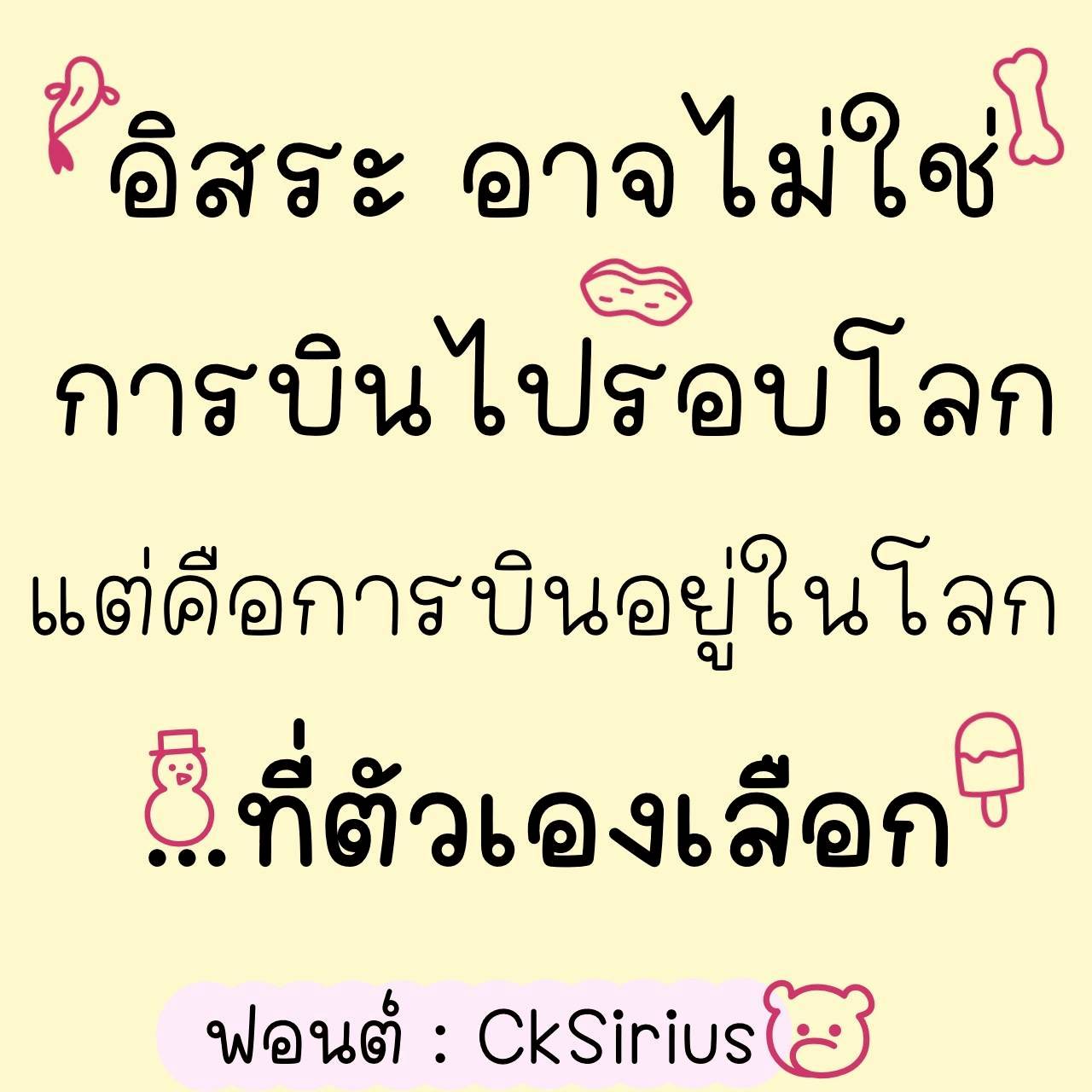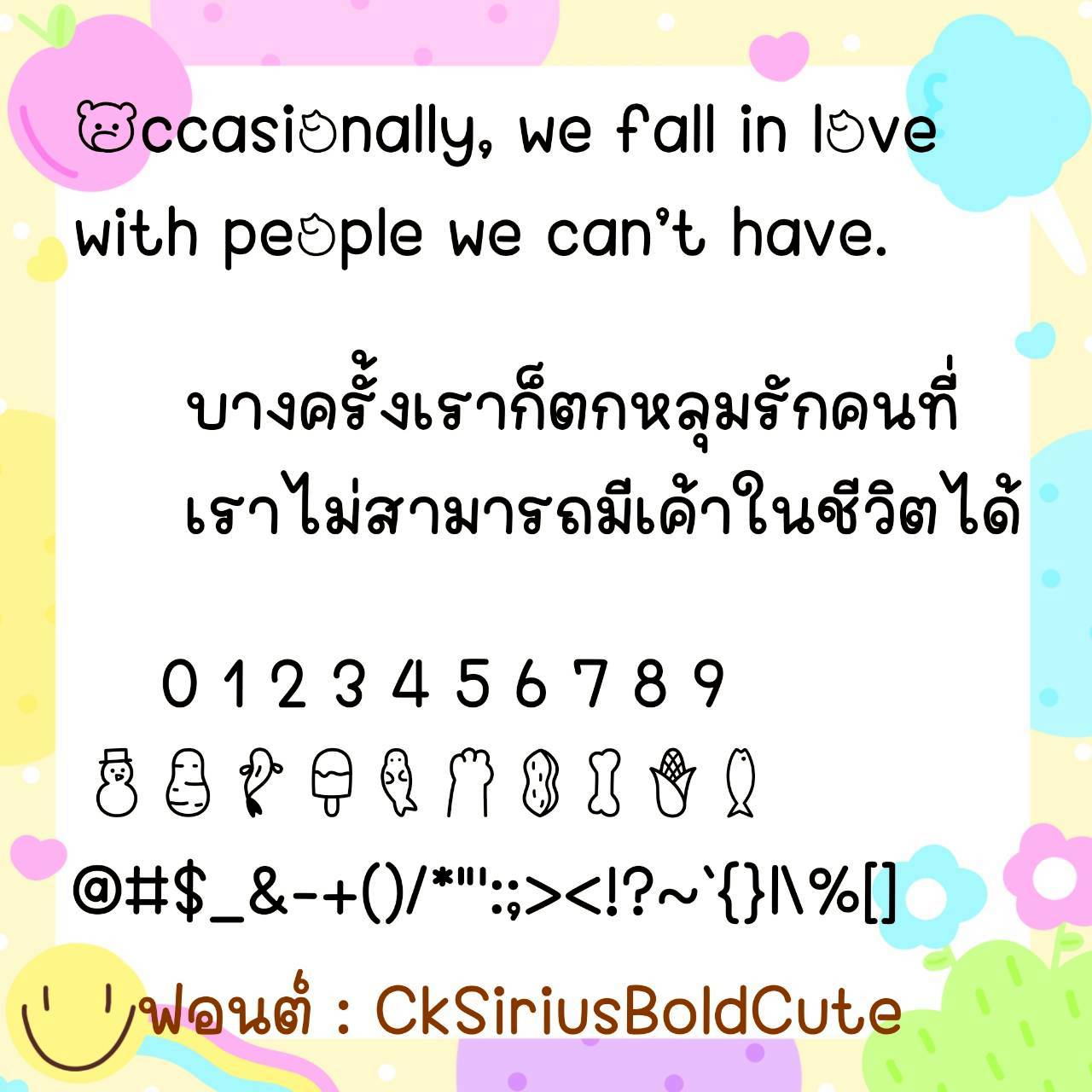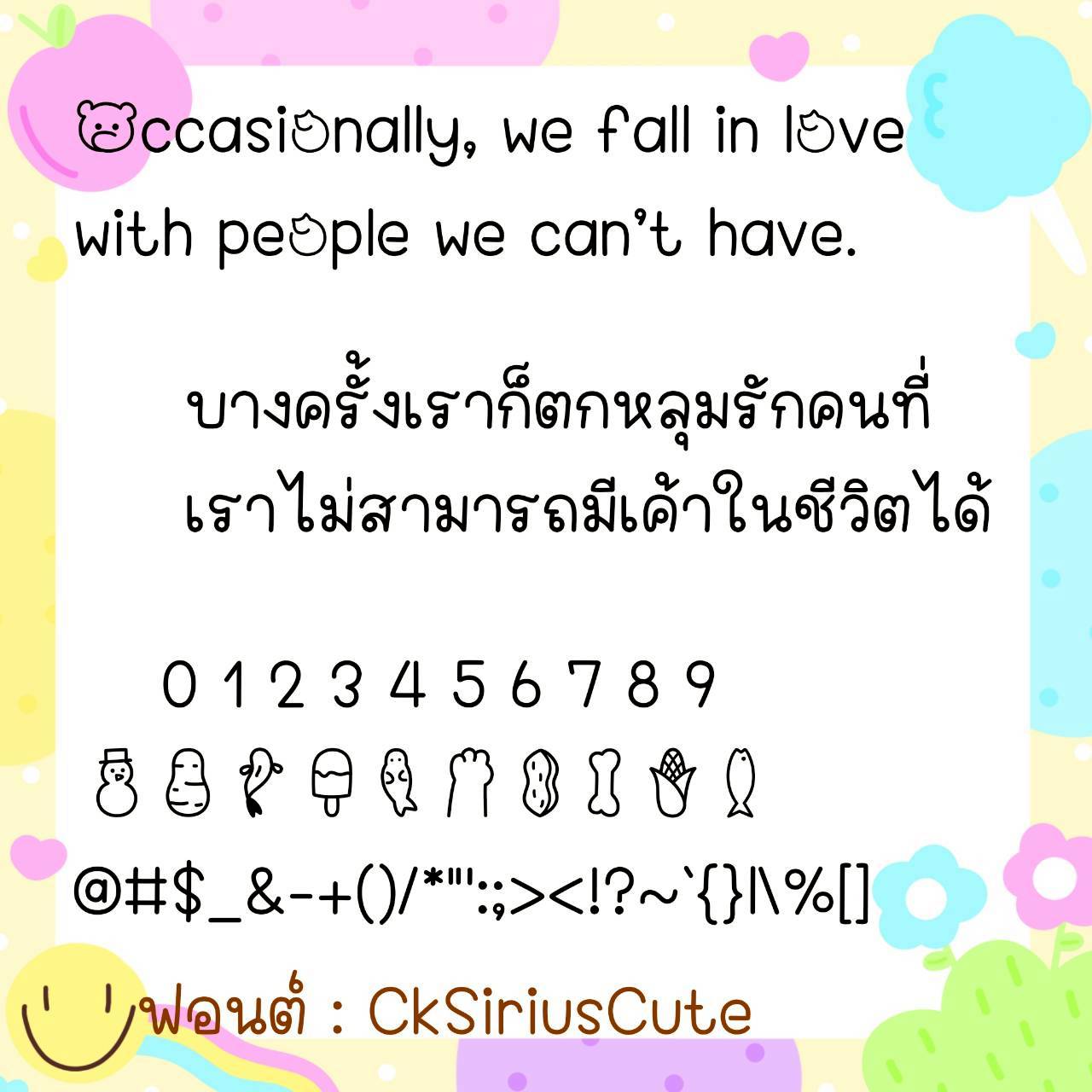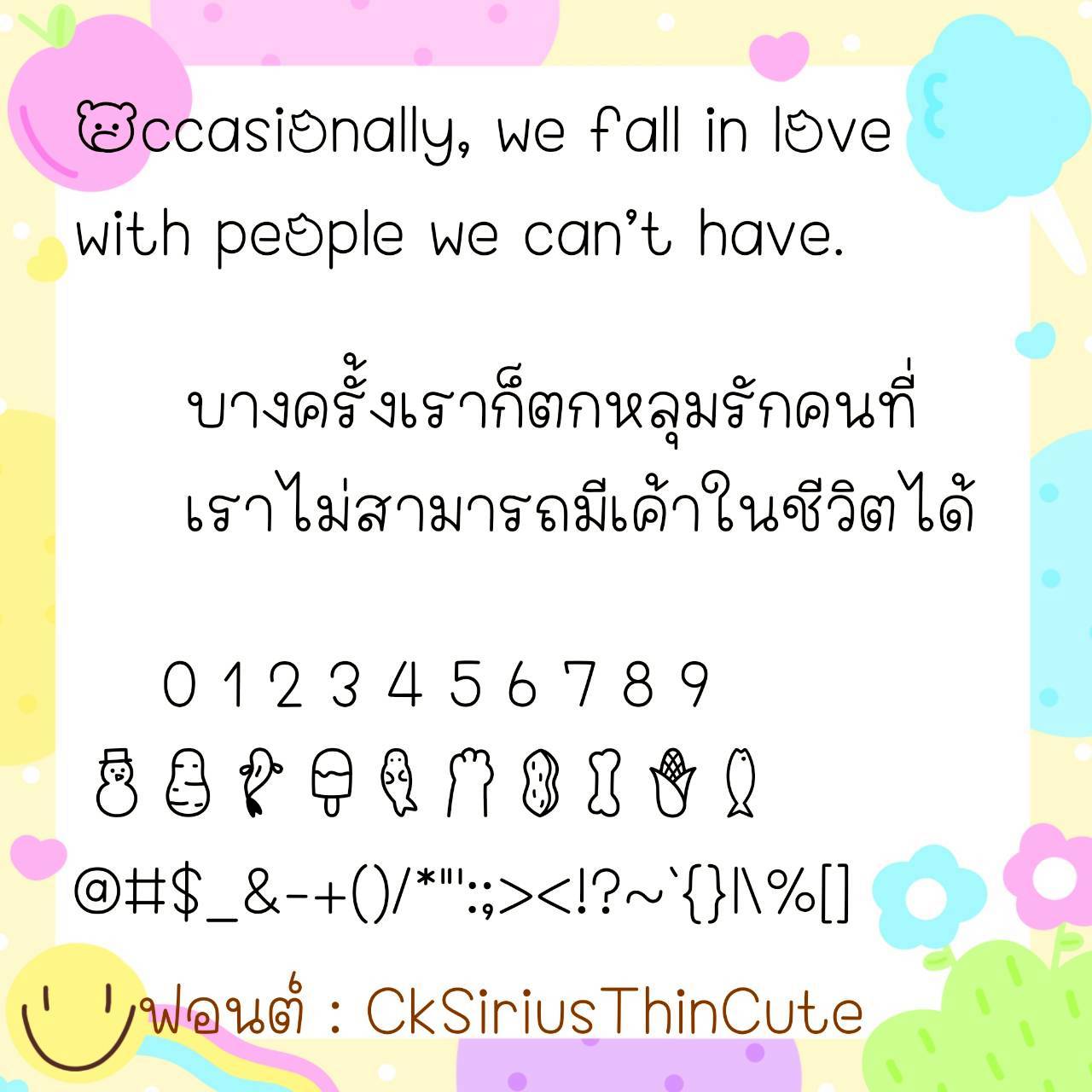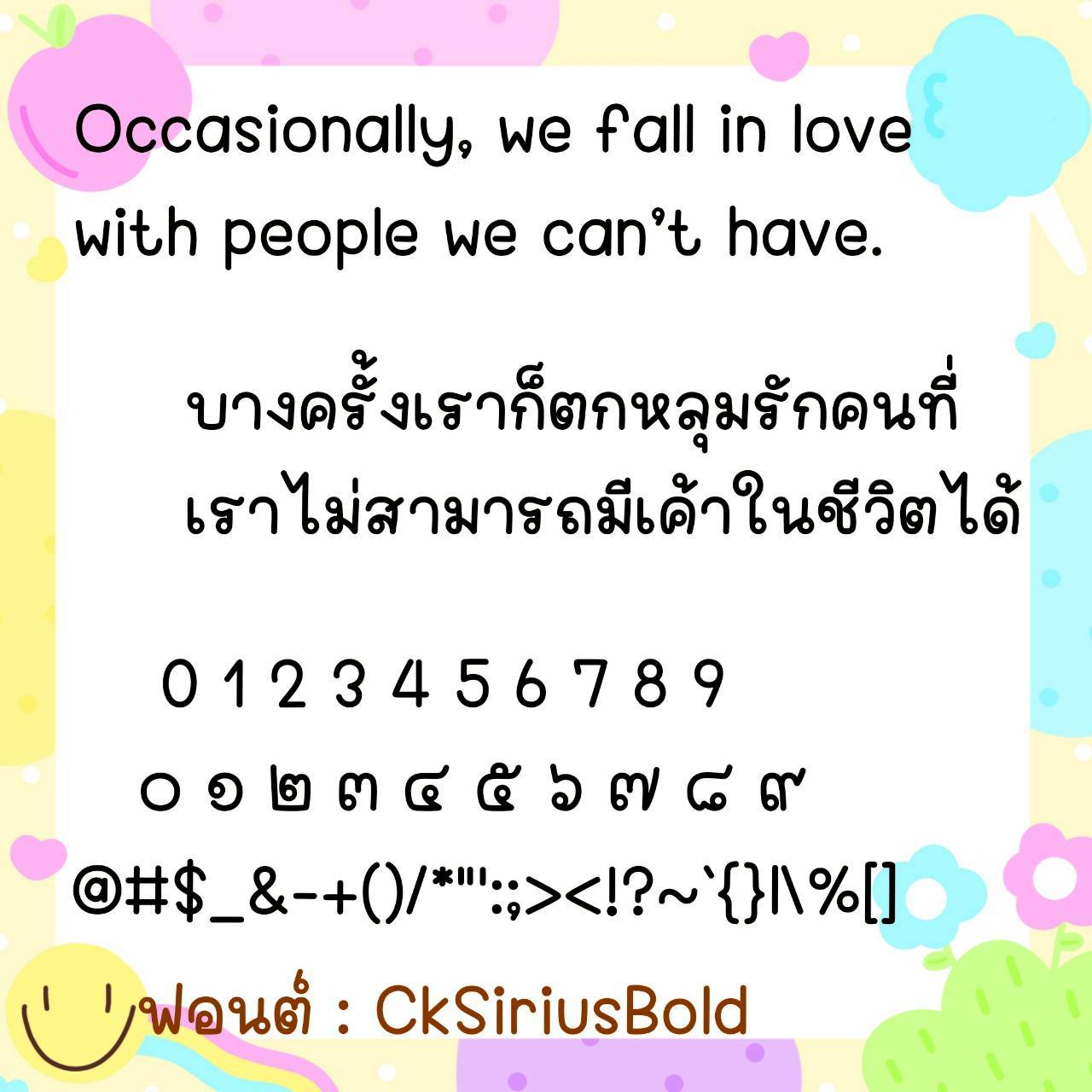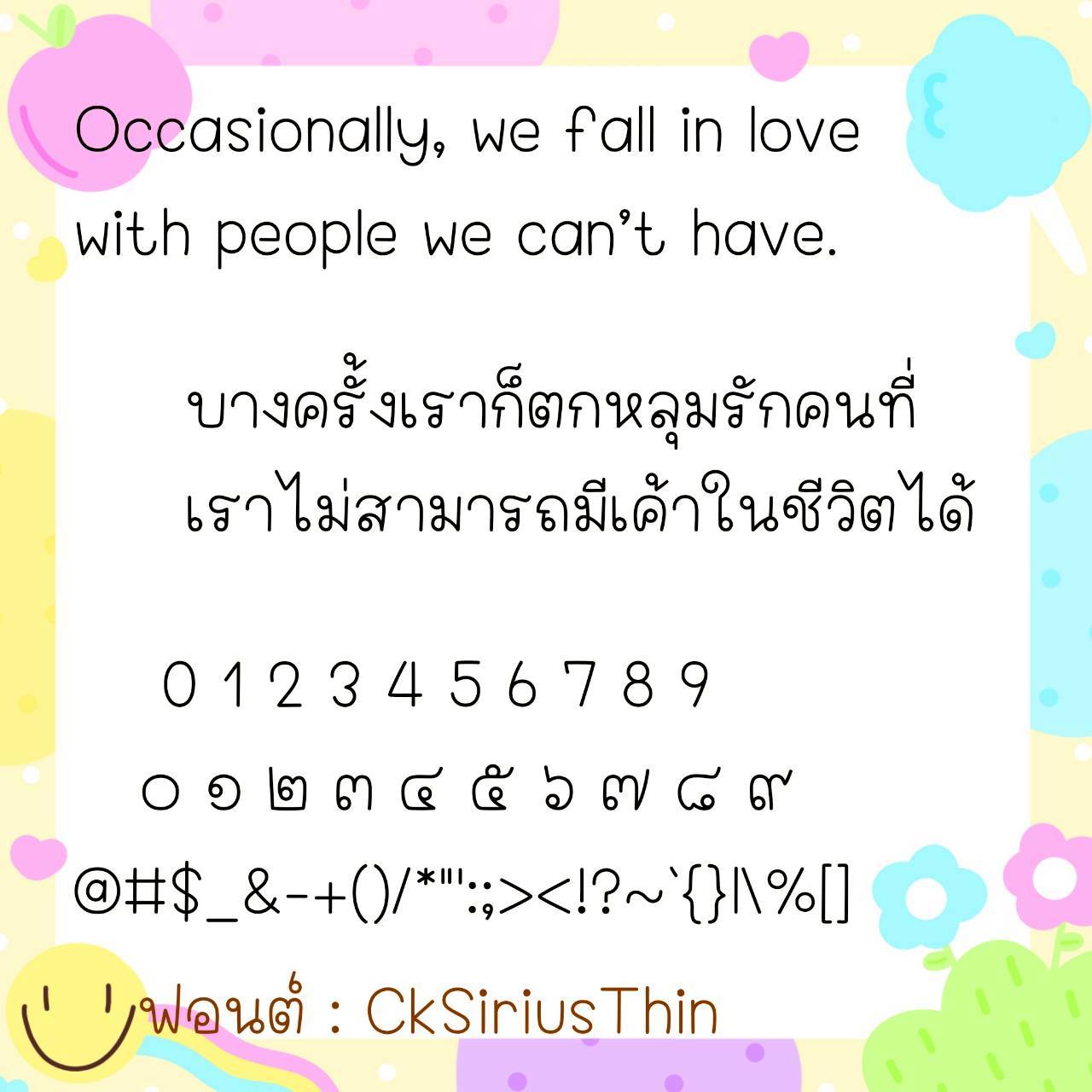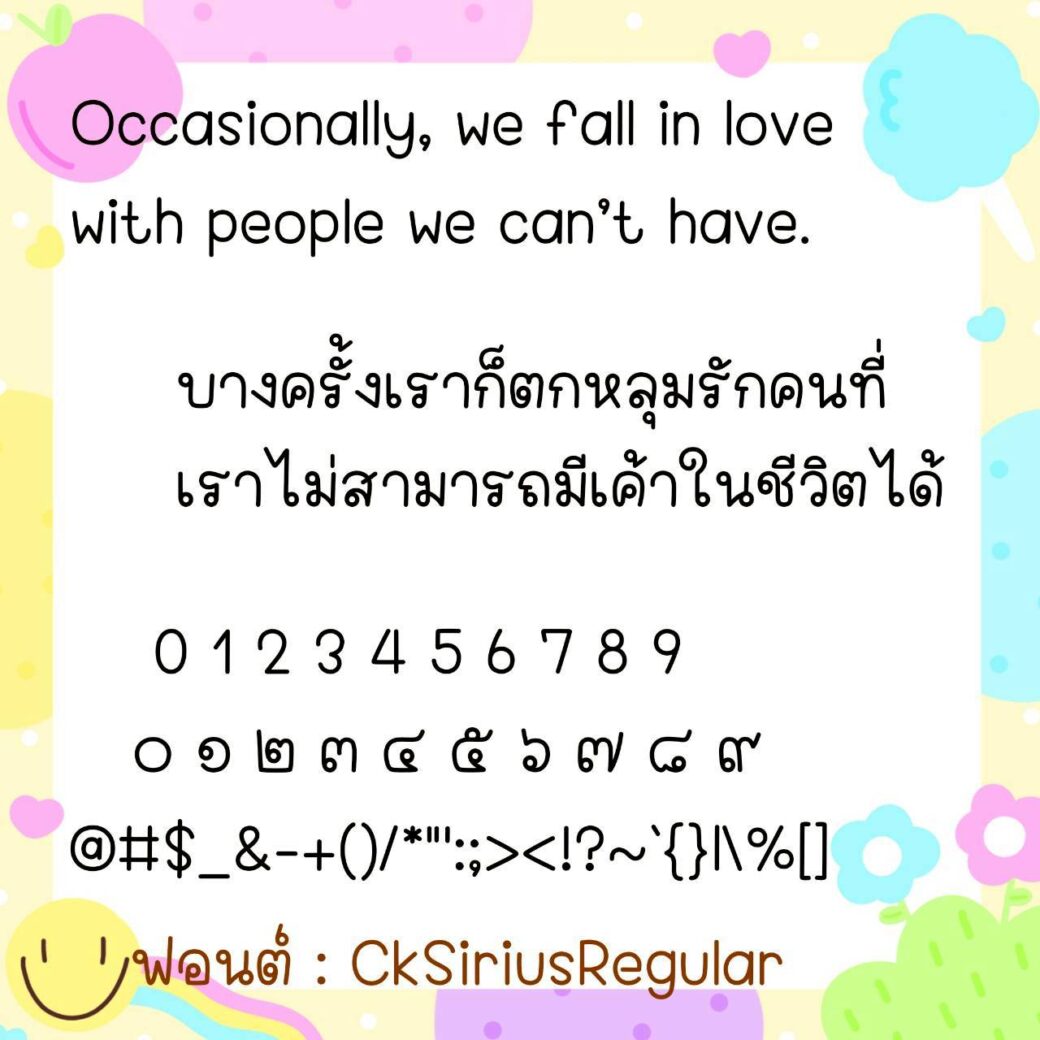
Font CkSirius
🔸 ฟอนต์ลายมือแนวน่ารัก ดูมีลูกเล่นตามสไตล์วัยรุ่น ตัวฟอนต์อวบๆ เน้นอ่านง่ายสบายตา และยังมีไฟล์อิโมจิน่ารักๆที่ใช้แทนเลขไทยให้ด้วยค่ะ 🥰💙
🔹 This cute, handwritten font has a playful, youthful style. The chubby font is easy on the eyes and readable. It also includes cute emojis that can be used to replace Thai numerals. 🥰💙
🔸ฟอนต์ลายมือแนววัยรุ่น มีความยึกยัก น่ารักมีสไตล์ดูมีลูกเล่น ดูไม่น่าเบื่อ และยังมีไฟล์อิโมจิน่ารักๆที่ใช้แทนเลขไทยให้ด้วยค่ะฟอนต์ปรับสระเรียบร้อยไม่ลอย ไม่เหลี่ยม ใช้งานได้กับทุกโปรแกรม ได้ทั้ง ios(รองรับกับแอพต่างๆที่รองรับฟอนต์ในios เช่น Goodnote, Procreate)/android/คอมฯ/Ps/Word,Excel ได้หมดจ้าาาาา❤️❤️❤️